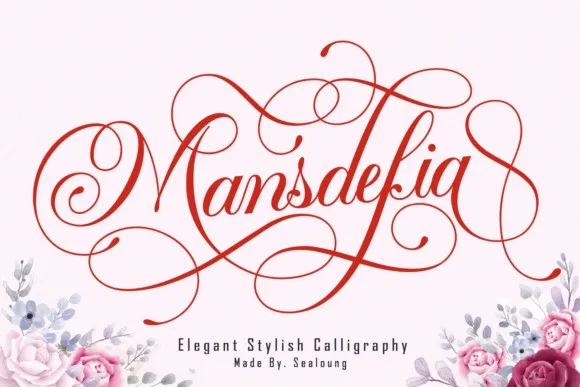
A Mansdefia Font é uma linda tipografia script criada pelo designer Sealoung. Essa fonte foi meticulosamente cuidada, oferecendo detalhes impressionantes e perfeitos para uso em diversos ambientes. Inspirada no traçado feminino do handwriting italiano e nas antigas obras literárias manuscritas, ela se adequa a uma variedade de aplicativos desde capas de livros até cartões de aniversário e logotipos, além de muitos outros usos criativos. Seu formato PUA (Unicode) facilita o acesso a todos os símbolos e espelhamentos necessários para um uso fluido. A Mansdefia Font é perfeita tanto para quem busca personalidade em seus materiais quanto para aqueles que desejam uma aparência sofisticada e elegante em suas criações digitais. Seja você criando cartazes, design de web ou apenas preparando letras para um projeto de arte gráfica, essa fonte tem o potencial de tornar sua experiência na criação ainda mais divertida e versátil.